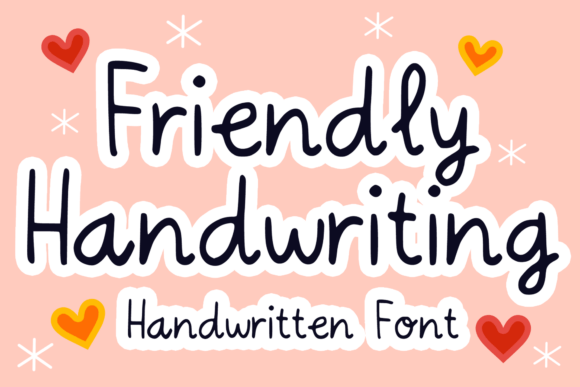
Friendly Handwriting
Friendly Handwriting – A Fonte Que Transforma Texto em Emoção
Se você procura uma tipografia que una alegria, calor e legibilidade, a Friendly Handwriting é a escolha certa. Criada para lembrar os rabiscos de um caderno de anotações feito com carinho, esta fonte manuscrita traz à tona a personalização que falta em muitas composições digitais.
- Estilo casual e claro: letras arredondadas que mantêm a leitura fluida mesmo em tamanhos menores.
- Traços cheios de personalidade: cada curva parece desenhada à mão, transmitindo playfulness e sinceridade.
- Versatilidade de uso: ideal para livros infantis, cartões de felicitação, diários, stickers, posts de redes sociais e qualquer projeto que exija um toque humano.
- Alta legibilidade: apesar do visual descontraído, a fonte preserva a clareza, evitando confusões típicas de fontes manuscritas excessivamente estilizadas.
Por Que Escolher Friendly Handwriting?
Em um mundo onde o design digital muitas vezes parece frio e impessoal, a Friendly Handwriting devolve a sensação de um bilhete escrito à mão. Essa característica a torna perfeita para:
- Comunicações que visam criar conexão emocional com o público.
- Projetos que precisam destacar criatividade sem perder a clareza.
- Marcas que desejam humanizar sua identidade visual.
Aplicações Práticas
Veja como a fonte pode ser aplicada em diferentes contextos:
- Livros infantis: ilustrações de texto que parecem escritas por um amigo de confiança.
- Cartões de felicitação: mensagens de aniversário ou agradecimento com toque pessoal.
- Jornais e diários digitais: entries que parecem escritos em papel.
- Stickers e merchandise: slogans curtos que saltam aos olhos.
- Posts de Instagram e TikTok: legendas que se destacam no feed.
A Friendly Handwriting vai além de ser apenas uma fonte; ela é uma ferramenta de storytelling visual. Ao escolher essa tipografia, você garante que suas palavras ganhem vida, transmitindo amizade, alegria e autenticidade. Experimente hoje mesmo e descubra como um simples detalhe tipográfico pode transformar completamente a percepção do seu público.